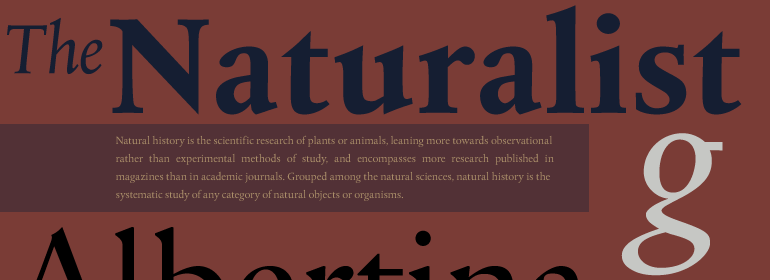
Albertina™
Albertina™,这款字体结构工整、笔画清晰,兼顾美观与易读性,适用于标题、正文、海报、包装、LOGO 等多种场景。字形优雅稳定,风格百搭耐看,适配日常排版与创意设计,让文字呈现更舒适、更具质感。Albertina™一笔一画,皆是细节,以均衡的比例、流畅的线条打造舒适视觉体验,字形端正大气,风格简约现代。无论是商业设计、品牌宣传还是日常排版,都能轻松驾驭,让文字更有格调与力量。Albertina™字体下载。
字体品牌: Monotype 设计师:Brand,Chris; Blokland,Frank E. 字体分类:衬线体 字体属性:外文 字符集:Unicode 发布时间: 2018